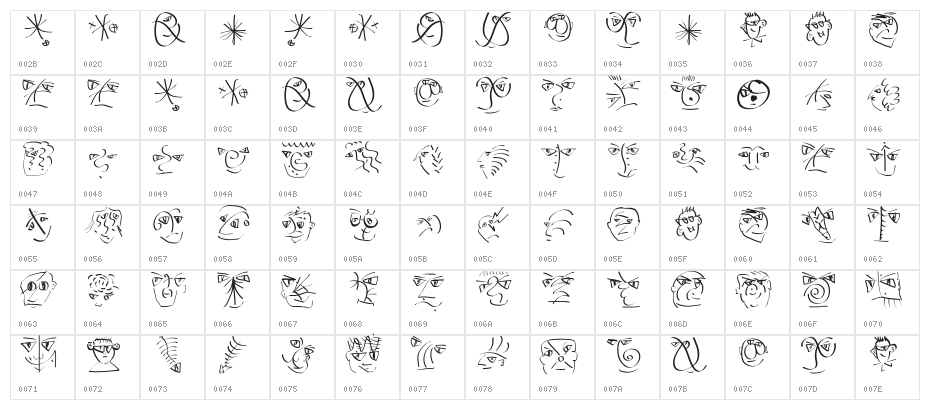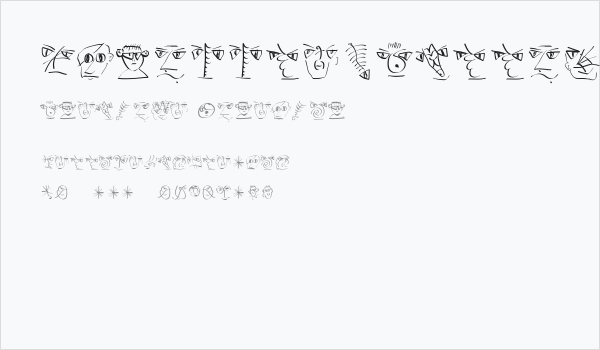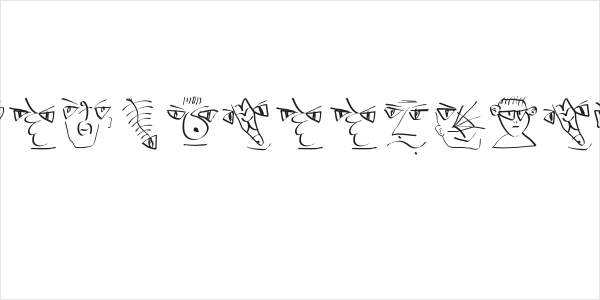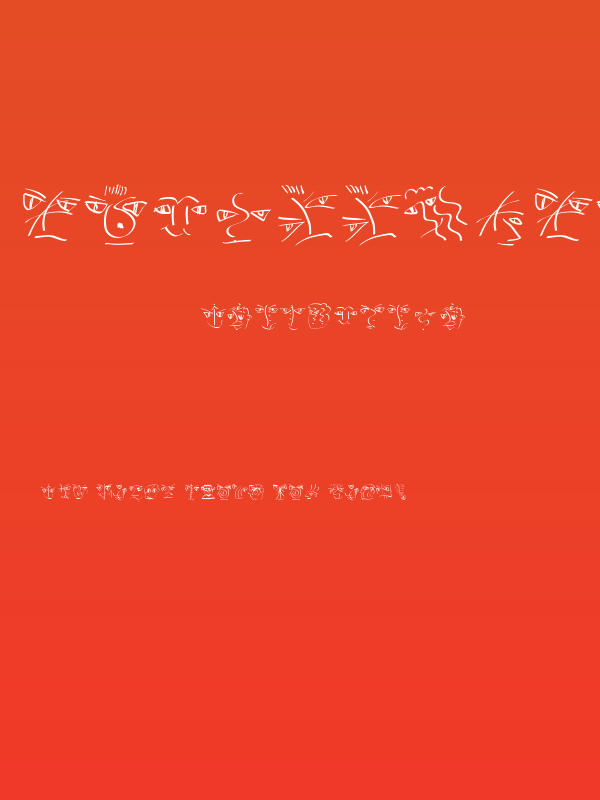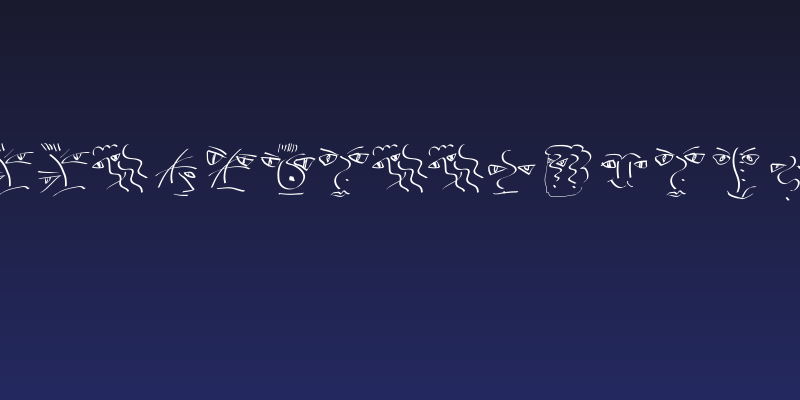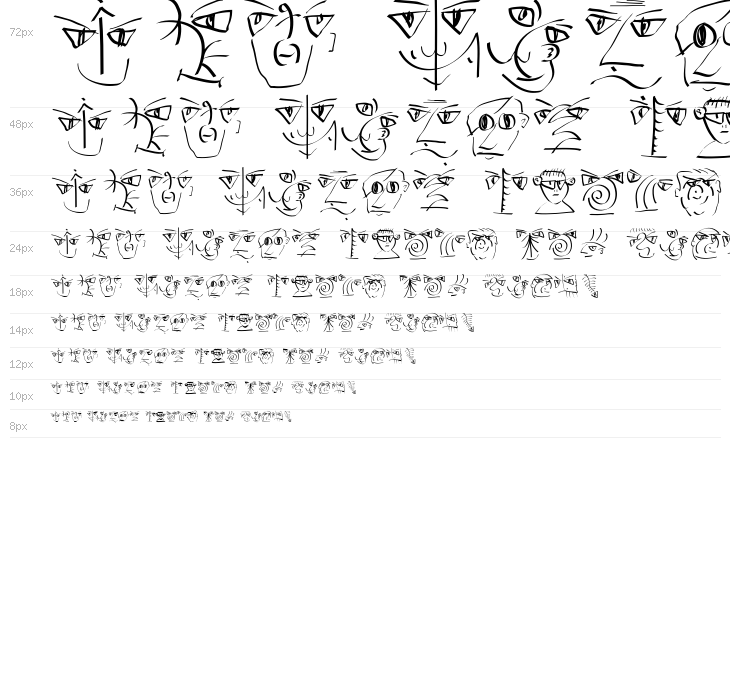
ScribblesCalligraphique Font
| 用途 | Logos, Art projects, Posters |
| おすすめプロジェクト | Ideal for creative projects such as art posters, children's book illustrations, unique branding, or any design requiring a playful and artistic touch. |